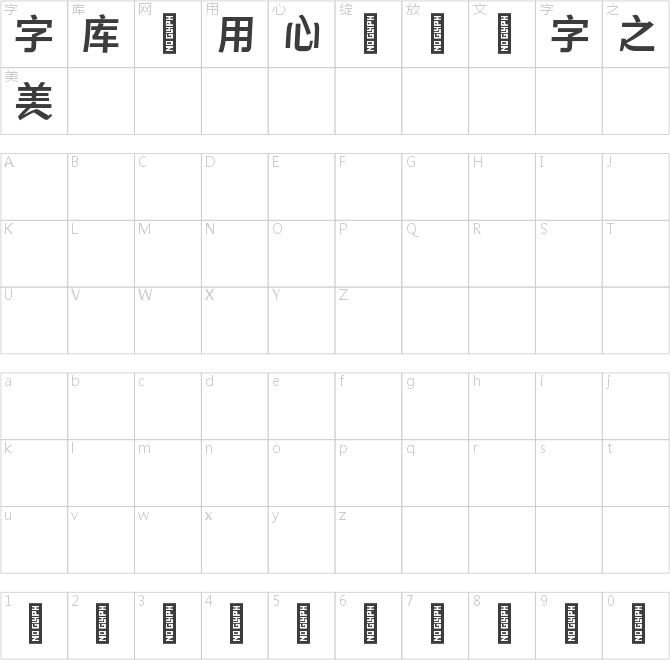
詠樂體字體下載字語詠樂體yongleti Regular
詠樂體字體字語詠樂體yongleti Regular字庫是一款讓人賞心悅目、百看不厭的中文字體,適合各類廣告和產(chǎn)品包裝設(shè)計(jì)應(yīng)用,字體大小0.05MB,格式為ttf字體,上傳用戶是快霸中國,作者/版權(quán)方為字語字庫